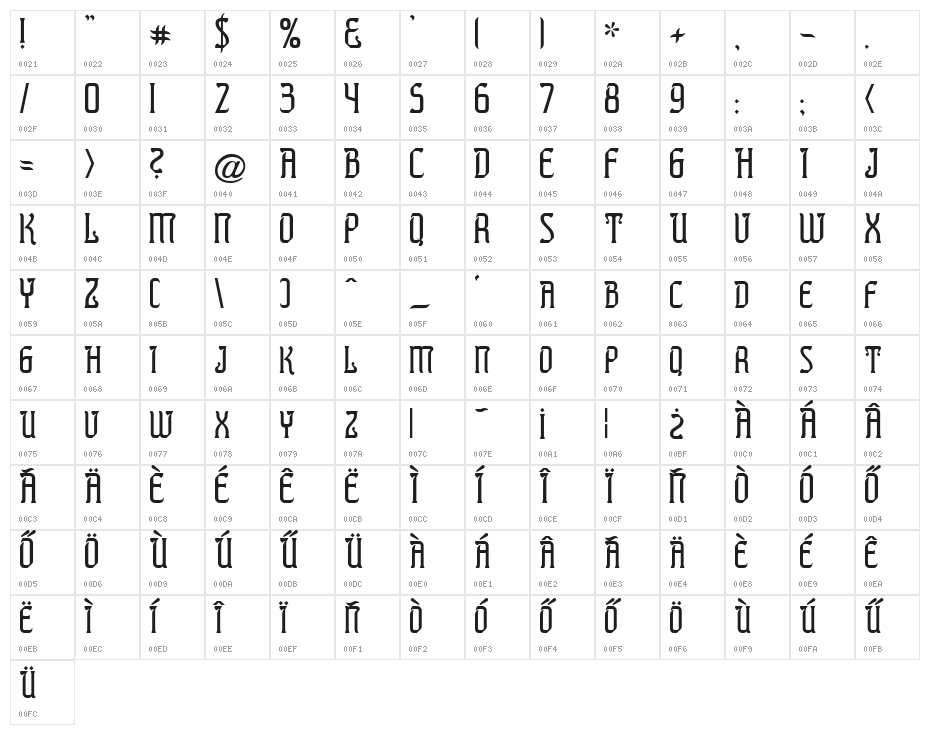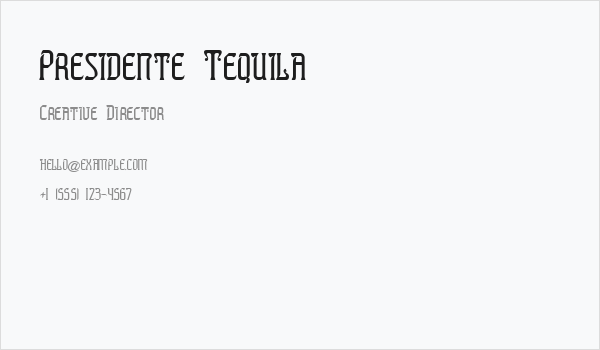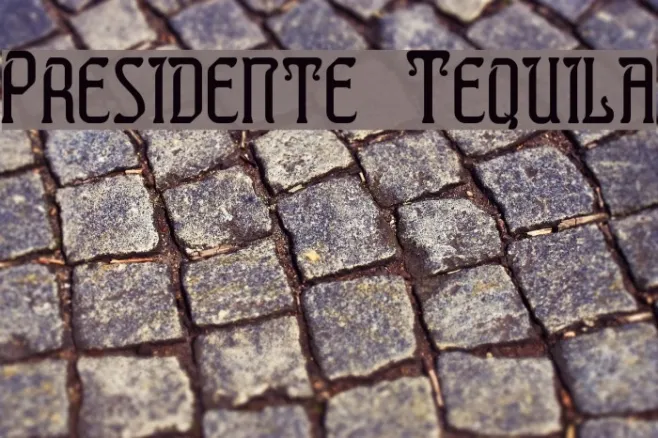
Presidente Tequila Font
このフォントには 146 文字が含まれています。文字をクリックして詳細を表示。
| 用途 | Headlines, Logos, Branding |
| おすすめプロジェクト | Ideal for branding, logo design, packaging, and headlines that require a strong visual impact. |